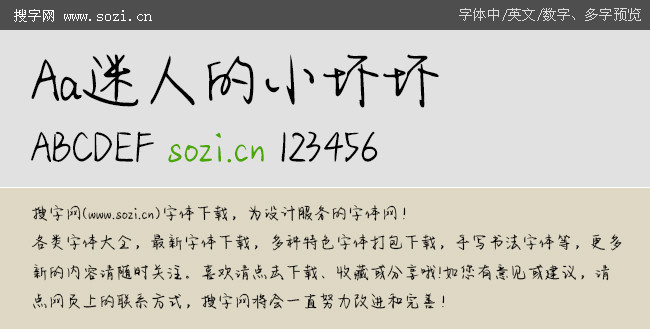
Aa迷人的小壞壞字體
搜字網(wǎng)給大家提供一款A(yù)a迷人的小壞壞字體中文字體下載,這是一款手寫風(fēng)格的書法字體,字體書寫自如,效果瀟灑大方,適合海報設(shè)計、包裝畫冊等宣傳廣告等應(yīng)用(此字體為個人非商用版,如需商用請聯(lián)系作者購買版權(quán))。